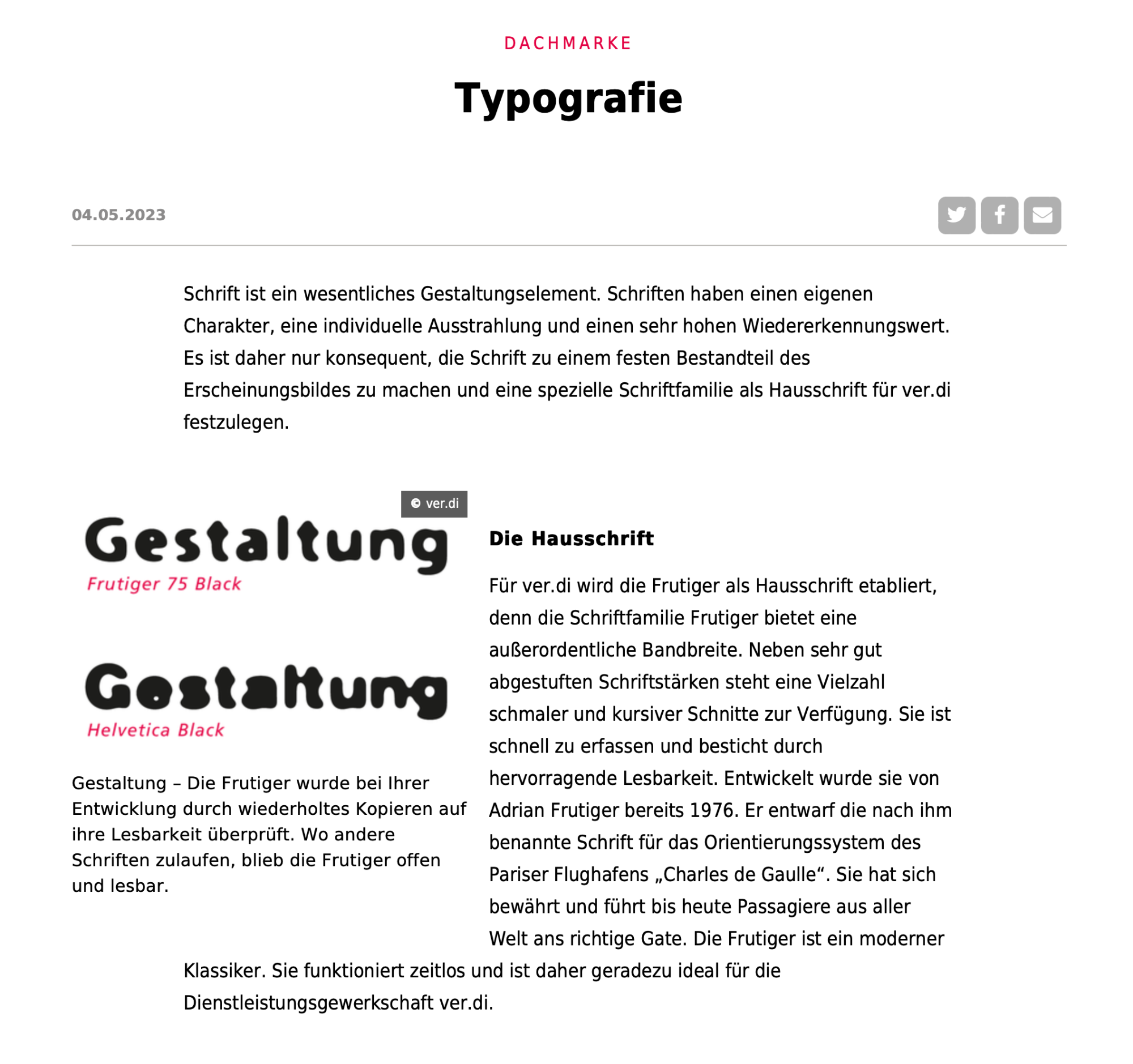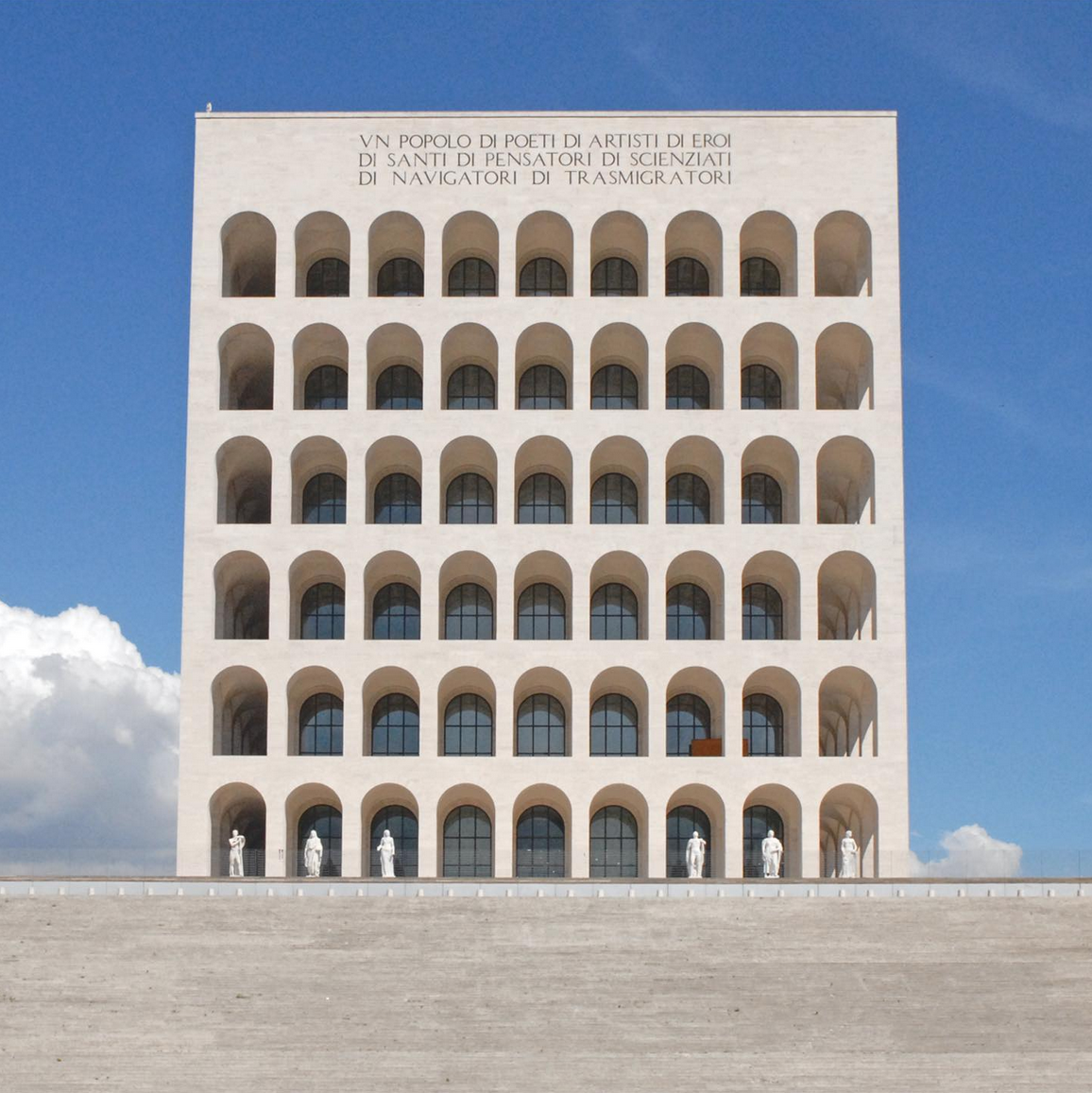
alt, aber nicht ganz romanisch (Fiesole, Italien)
Die weichgezeichneten Schnitte der Frutiger und Helvetica kannte ich noch gar nicht. Aber wahrscheinlich wurden die individuell für ver.di erstellt ...
Und das sogar ganz analog durch »wiederholtes Kopieren« (damit werden sie kaum die Dateien gemeint haben). Die Poschaukos wären beeindruckt.
Kannte ich bisher nicht: Palazzo della Civiltà Italiana (Colosseo quadrato) in Rom, heute Fendi-Headquarter.
»Die Anzahl der Rundbogenarkaden entspricht senkrecht (sechs) der Anzahl der Buchstaben im Namen Benito und waagerecht (neun) Mussolini.«
Die Inschrift ist allerdings kein typografisches Meisterwerk. :shock:
Vor allem fühlen sich die letzten beiden A sehr einsam … ; )